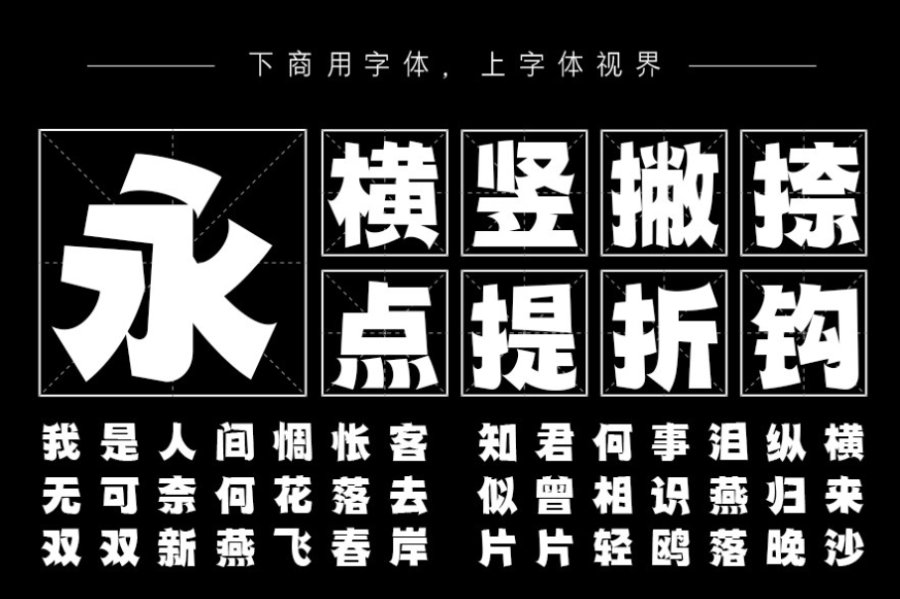
一款个人免费商用的字体——楚辰体
2020年伊始,字体君给大家带来了一款个人免费商用的字体——楚辰体;
“楚辰体”的字能在轻松时尚的氛围中体现,粗黑为字形基础,不规则的笔画,在排版时能表现跳跃的节奏感。轻快自然的特征能让标题和广告语更加醒目生动。该字由著名字体设计师丞言老师耗时2年独自完成创作,由字体视界对外公开首发,供个人免费商用,企业需付费商用授权使用。
楚辰体